中国风?这个词我们一定不陌生,你是先想到泼墨山水画还是周杰伦?我猜大家先想到后者,我的印象里杰伦的一首《东风破》将「中国风」这个词唱进我们的生活里,之后的音乐、电影、广告、家装、服饰等等都会看到中国风的印记。但你知道设计中国风的字体有哪些规律和方法吗?
首先要说明的是,今天所讲的中国风其实是一种字体设计的表现风格,就像描述字体风格还有现代简约、复古怀旧、卡通可爱等等一样,本次的主题说的再直白一点就是设计中国风的字体有哪些规律和方法!
那到底什么是中国风?我想每个人的理解都会有所不同,但你脑海里首先蹦出来的肯定是「传统」这个词,再来看看百科的释义:“中国风,即中国风格,是建立在中国传统文化的基础上,蕴含大量中国元素并适应全球流行趋势的艺术形式或生活方式”。在字体设计中大家不要去管什么全球流行趋势,只要能够把中国元素合理的应用到字体中就足够了。
那么问题又来了,中国元素千千万该怎么用到字体设计中?上图中我简单列举了一些中国代表性的传统物件,虽说形式多样,但我们可以找到一个共同的特征:繁。
还记得我之前《字体性格知多少》一文中提到的一点吗?笔画越繁琐呈现出的字体性格就会更加古典传统。你看很多理论点都是有依据的,所以有些小伙伴们千万不要觉得理论无味无用,只顾着埋头设计而不知道为什么要这样做又有何道理。
上图中从上到下的字体笔画和细节都处理的越来越繁琐,最终呈现的视觉效果会越发有中国风的感觉。如果「繁」是规律,那么具体方法又有哪些呢?下面我总结了四点与大家分享。
特别提示:繁是建立在传统元素的提炼基础上,不是多、不是杂、更不是乱,不要理解跑偏了。
笔画的细节修饰是最能够直观准确的表达字体性格的,就像京剧里面脸谱的色彩图案与角色的性格有密切的关联。我们可以简单理解为做字体的表面文章,那么怎么样的细节修饰才能够体现出中国风呢?
前面我们讲到了中国风一定是建立在传统文化基础之上的,那么我们就一定要结合传统元素。最常见的莫过于古建筑中的飞檐翘角了,当然还有一些祥云图腾或是回纹等,下面我用这些元素做几个小例方便大家理解。
飞檐翘角是中国古建筑里面极具特色的结构形式,表现出中国建筑的独特韵味,所以用到字体中再合适不过。其中用于笔画中的横笔起笔与收笔之处,上图中的文字在横笔和上部的折角做了类似「飞檐翘角」的处理,字体就会表现出浓浓中国风。
字体中的「飞檐翘角」可以有多种形式,上图中的字和上一例最大的不同是笔画用了线段的形式,但同样是使用「飞檐翘角」的形式,还有一点不同的是一些横笔没有做任何处理,这是为什么?我们一开始就讲到了,繁可不是多更不是乱,要根据字型掌握好度。
这一组字最大的特征是用到了祥云元素,或许很多同学会说这哪里像了,这里我想很多朋友会有一点误区,在做字体修饰细节或是加一些图形的时候,一定要简练概括并能够和字体有很好的契合,所有的变化都是要服务于字体本身。
我们常见的是横平竖直的笔画,如果将笔画做一些形变字体最起码是有别于我们印象中的常规字体,笔画的形变其实也是字体设计中常用的手法之一,但是关键在于如何让它变得有中国味道。
传统物件中如瓷器和中式座椅,形态是让人印象深刻的也极具代表性,所以我们可以套用其中的一些基础形态用到字体设计中。
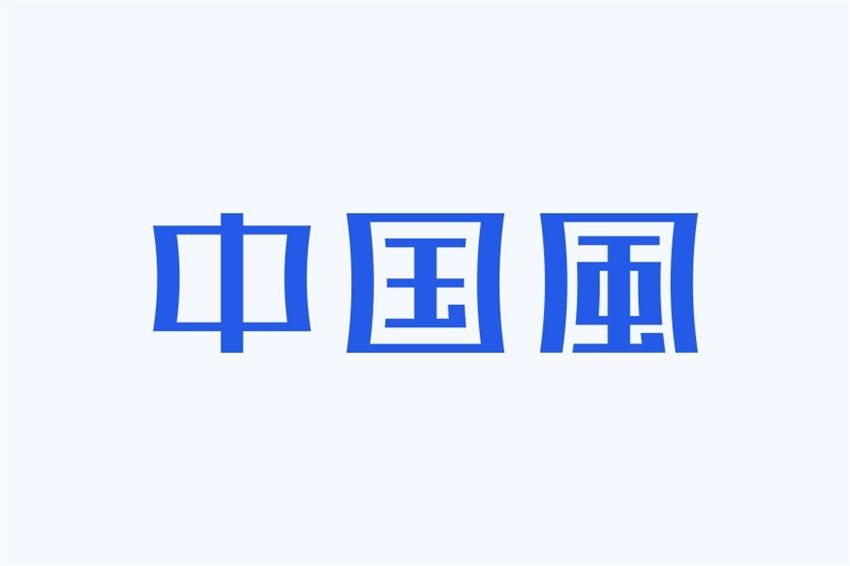
上图中在没有任何笔画修饰的情况下,我们把字体中的竖笔做了简单地形变,由垂直的竖笔做了一定的内收弧度,这是最简单的形变。
这组字的形变就稍稍复杂了一些,笔画的细节也多了一些断笔和类似「回纹」元素的处理,这种变形除了有中国味道,也多了几分女性化的柔美。此类形变是有规律的,所以大家可以直接用Ai中的效果-变形工具即可快速完成。
上面依然是横平竖直,可到了字体的下端变成近似圆形,结合一些横笔小细节的变化整个字的结构也刻意做高,除了有中国味道,品质感也会有所提高,所以这种形变貌似很多小区的标志喜欢这样用。
上图中就巧妙的结合了老式家具的样式,让字体变得非常有画面感。传统器物中还有很多有趣的元素可以用到字体设计当中,大家不妨挖掘一下,看看可以创造出哪些有趣的字体设计作品。
如果条件允许,大家可以尝试一下繁体字的设计,繁体字笔画本身就相对比简体多一些,也会更多一些年代感。有时候我们可以借鉴的更远一些,比如篆书,因为篆书保留着古代象形文字的特征,具有极强的装饰性。
特别要讲明的一点是,篆书虽好可不要完全照搬,因为篆书在今天没有多少人能够认得出来,也就是说识别性是有问题的,所以我们借鉴不是完全照搬,也要根据实际合理的调整,首先还是要保证文字的识别性。
可以先查阅一些古籍,找到你所要设计的文字,或者直接在网上字体在线查询。篆书笔画变化多且多曲线,上图中我保留了篆书的笔画形式,曲线改为直线,这样做可以让字体不至于年代感过于久远。
第二个字还是觉得有些复杂,特别是斜向笔画的穿插和其他笔画融合性并不如意,所以又进一步做了简化,最后效果如图,其实也还可以继续深入加入细节的刻画。
纯文字的标志中多加入一些辅助的图形,形式感会更强。
图形融入字体一般有两种方式:
字外,就是在字体的外部添加一个辅助的图形,不与字体内部的笔画有太多的关联。
字内,比如说将笔画直接换成某一种图形,这个处理起来自然也要麻烦一些。
园林中的窗、门或是国画中的印章都是图形很好的元素提取方向,这些图形大多是作为字体外部的图形起到一个强调的作用。像梅兰竹菊、龙凤等等这些比较有代表性的动植物也可以巧妙地结合到字体设计中,下面我们以窗为元素图形做个示例。
简单列举了一些中式窗的形状,只是看图形就能感受到浓浓中国风,如果现实中看这些窗真的是诗情画意。大家选用窗型的时候尽量选择简明一些的,有一些窗型太复杂,如果里面再加上复杂的中文字,视觉效果就会有些杂乱,这一点要注意。
要充分利用图形的特点,并且要让文字的笔画和图形有良好的位置关系和穿插,说的话看似挺简单,其实做起来还是有一定难度的,这需要大家多在草稿纸上涂涂画画。如果说某一种图形和文字就是无法很好地结合,那么建议果断的换种图形,思路或许就会瞬间打开。